Interactive animations with variable fonts 可變字型的互動式動畫
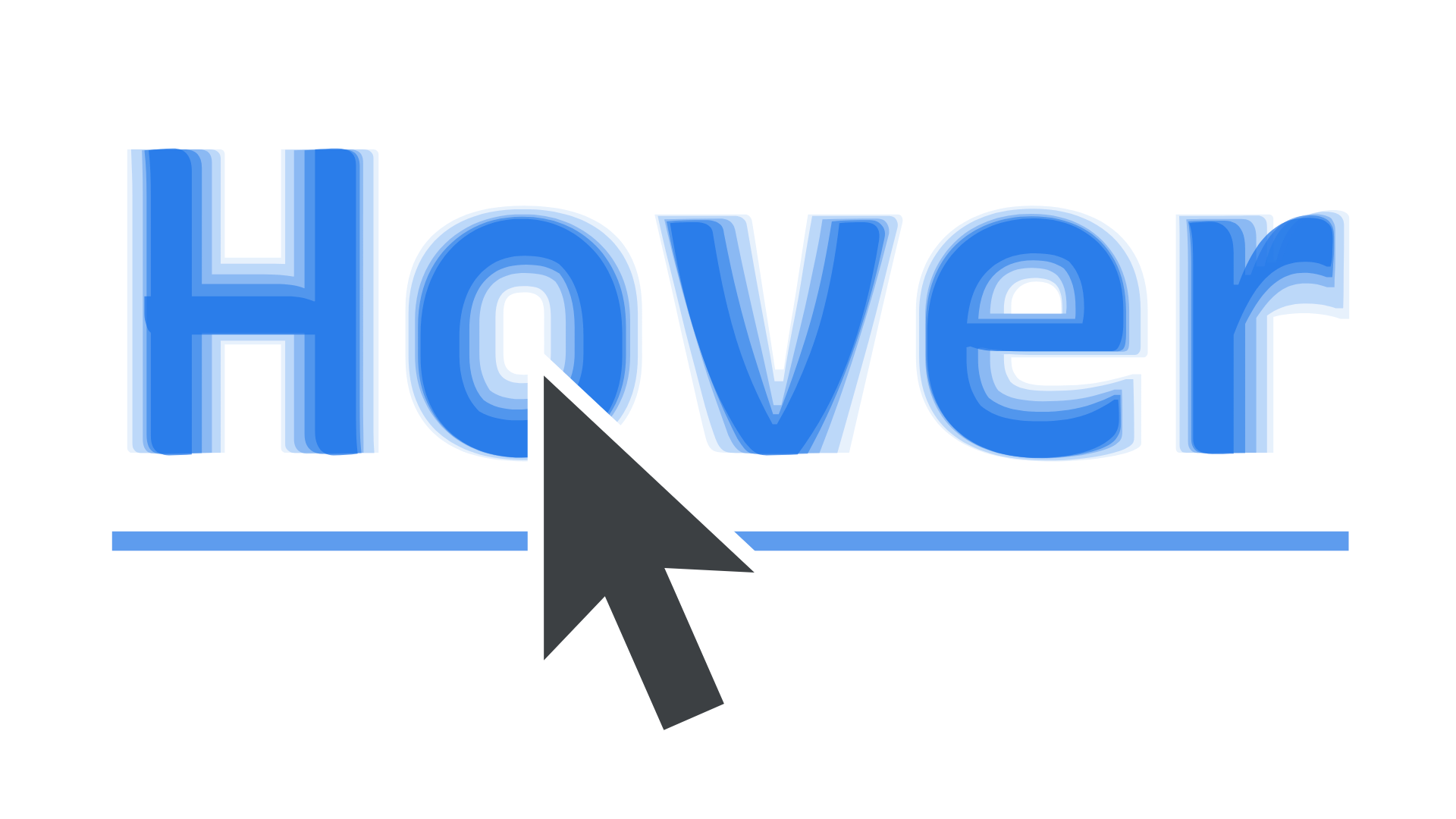
變數字型是一種特殊的字型格式,它可以讓字型在不同樣式之間平滑過渡,非常適合用來製作簡單的動畫效果。
Simple Hover Effects 懸停效果示例
當滑鼠懸停在連結上時,字型會改變粗細。普通字型在懸停時會突然變化,但使用變數字型可以讓這個變化變得更加平滑自然,使用的字型:Newsreader。
使用變數字型可實現平滑懸停效果,變化更加自然。注意控制動畫時間,避免影響體驗。字型變粗可能導致佈局偏移,特別是在選單等小型元素中。
將每個元素放在固定容器中,避免佈局偏移的懸停動畫效果。
Multiplexing Beyond Weight 等寬字型與字重調整
在一些情況下,我們不希望字型變化時影響佈局,
等寬字型可以讓不同粗細的變體佔用相同空間寬度,使懸停效果更流暢,同時避免佈局變化。它可以在不影響字型寬度的情況下調整字型的視覺重量。
Multiplexing Beyond Weight 字型變化的多種可能性
變數字型不僅可以調整字重,還能實現更多有趣的變化效果。比如有些字型可以調整斜體樣式而不影響字間距,還有一些字型提供更獨特的變化效果,讓設計更加生動。使用字型:Cheee Variable。
製作互動效果時,懸停不僅限於連結。您可以用span標籤包裹任意元素來觸發懸停效果,還可以調整過渡時間來控制動畫速度。